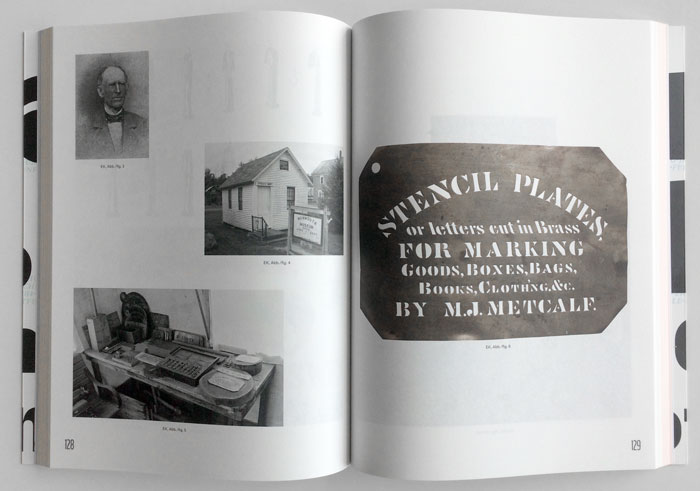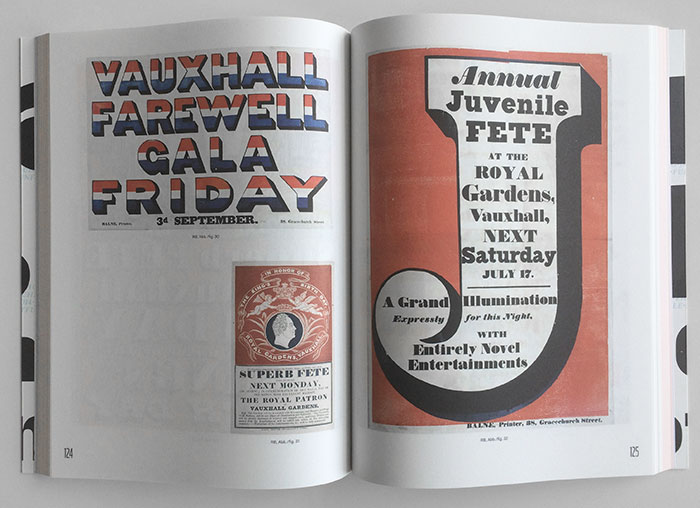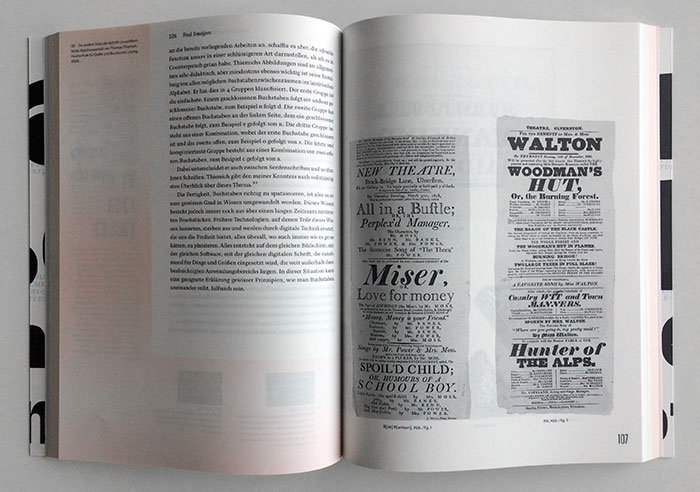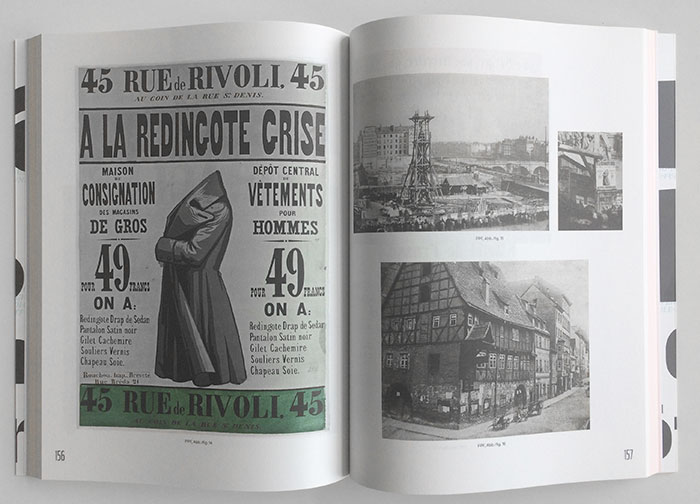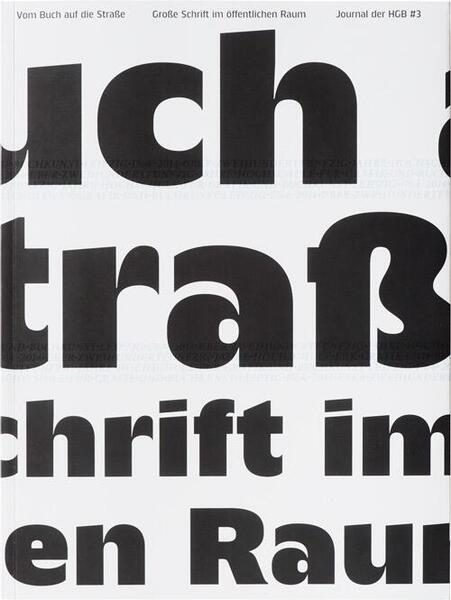
»Vom Buch auf die Straße. Große Schrift von 1600 bis 1920« war der Titel einer Ausstellung im Druckkunst-Museum Leipzig im Jahr 2014. Unter der Leitung von Julia Blume, Pierre Pané-Farré und Prof. Fred Smeijers (der Hochschule für Grafik und Buchkunst Leipzig) recherchierten Studenten der Fachklasse Type-Design nach bildlichen Zeugnissen, die die visuelle Kraft und den Facettenreichtum von Schrift von 1600 bis 1920 darlegen. Die Ausstellung umfasste Plakate, Postkarten, Drucksachen und Fotografien sowie Objekte und Filme. Die Exponate und Recherche-Ergebnisse wurden in der Folge nun zu einem Buch zusammengefasst, das als »Journal der HGB #3« erschienen ist.
Nach drei kurzen Traktaten folgen ausführliche Fachartikel zum Thema der Ausstellung:
• Die allergrößten Schriften Englands. Holzlettern für den Akzidenzdruck zwischen 1800 und 1830. Rob Banham
• Die Schablonenstanze. Ein neues Werkzeug für ein altes Handwerk. Eric Kindel
• Was kam nach der Schwarz und Rot? Zur Entwicklung der Farbigkeit im Hochdruck-Plakat des deutschsprachigen Druckereiwesens zwischen 1827 und 1865. Pierre Pané-Farré
• Buchstaben aneinanderreihen. Ein geschichtlicher Überblick. Fred Smeijers.
Die Artikel sind in deutscher und englischer Sprache abgedruckt. Dazwischen gibt es eine über 70-seitige Bilderstrecke mit zugehörigen Abbildungen in hervorragender Abbildungsqualität.
Untertitel: Große Schriften im öffentlichen Raum